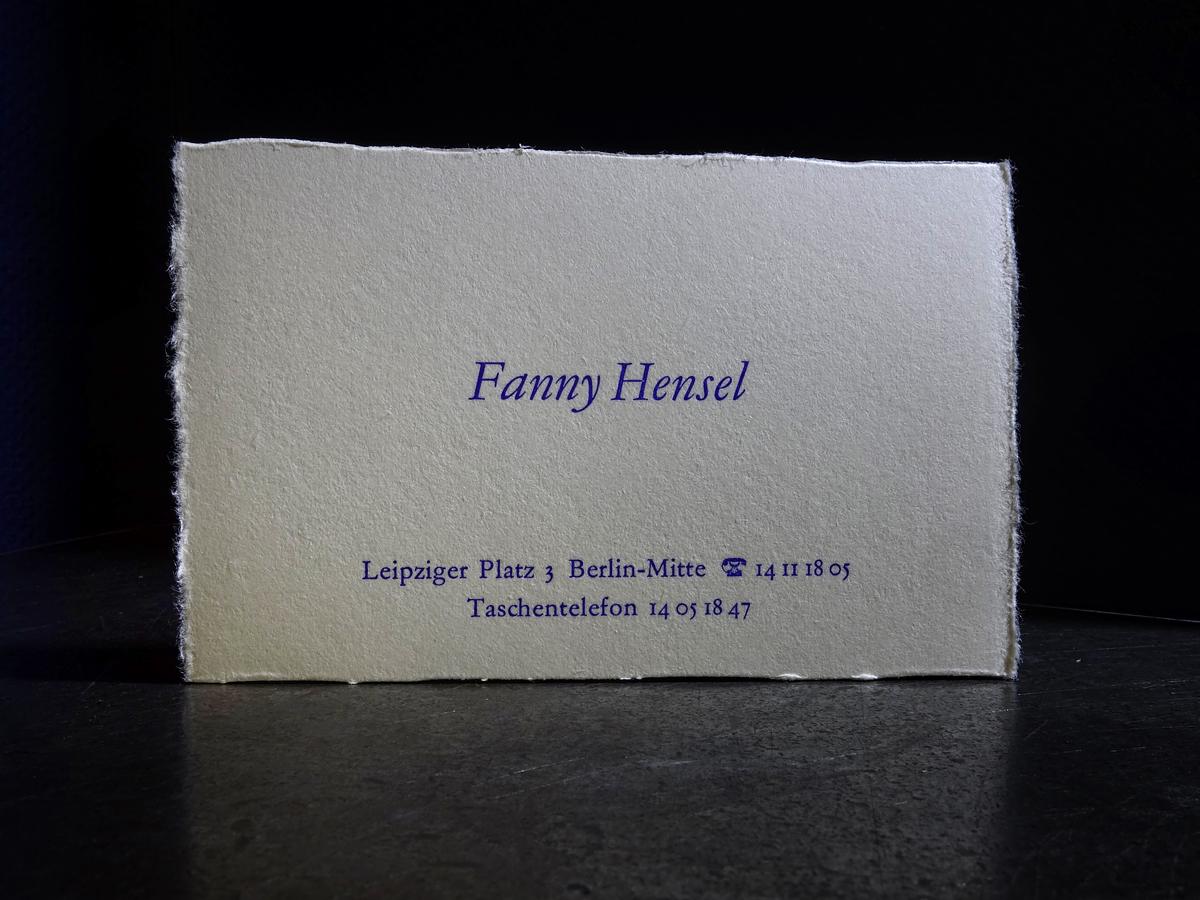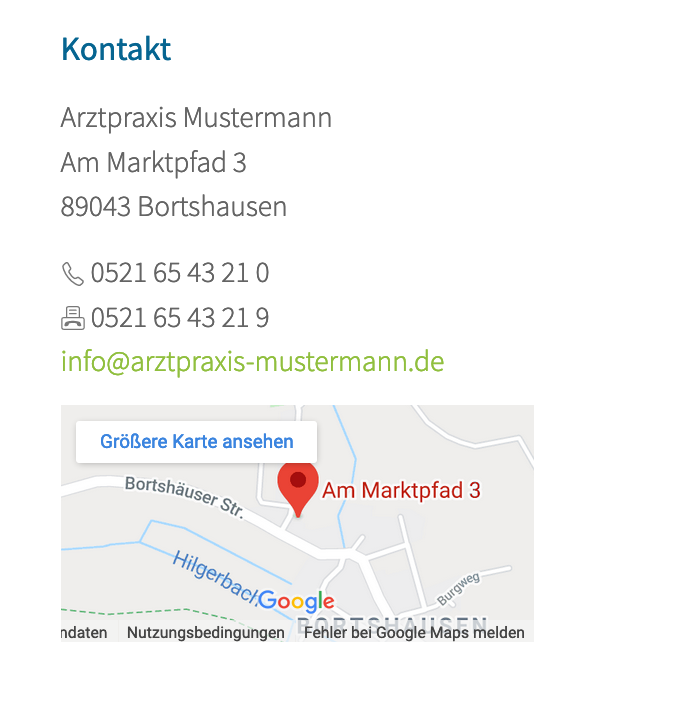
Kennzeichnung einer Faxnummer per Symbol?
Meinem Auge geht es wie Deinem. Ich finde  und erkenne die Information - in diesem Kontext - schneller als mit textuellen Etiketten.
Auf der richtigen Website lasse ich übrigens die URL weg, weil ich sie redundant finde.
Mit Hilfe eines Print-Stylesheets lasse ich sie beim Drucken erscheinen.
Auch ich belege nur die Telefonnummer und nicht die Faxnummer mit "href="tel:..."
Die Faxnummer erhält noch ein Title-Attribut, welches beim Überschweben "Faxnummer" anzeigt.
Zur Verspieltheit: Würdest Du denn soweit gehen, dass bei einer nüchternen Schrift, Farbgebung und Gestaltung generell Symbole für diesen Zwecke unpassend sind?
Wahrscheinlich ja. Zumindest bei einer ansonsten so nüchternen, technischen, sachlichen Gestaltung wie deiner hier. Decke ich die Symbole ab, habe ich diesen Eindruck. Der Symboleinsatz bricht das für mich völlig auf. Aber eben nur an dieser einzigen Stelle – der natürlich notwendigen Unterscheidung zwischen Tel.- und Faxnummer.
Wäre es meine Gestaltung, würde ich meinen, mich jetzt entscheiden zu müssen: entweder dazu, den kühlen Gesamteindruck so beizubehalten (dann eher ohne Symbole) oder die Anmutung bewusst, dann aber konsequent, etwas aufzuweichen. Das müsste dann aber an mehreren Punkten erfolgen. Und da finde ich die Idee mit mehreren Symbolen interessant.
Eine Sache, die ich in dem Zusammenhang übrigens immer hässlich finde, ist diese Geschichte:
Ihhhh! Da könnte man doch mit Symbolen arbeiten, z.B.
… und natürlich nur eine Zeile für beide Angaben. Und mit Symbolen aus einem Symbolfont, nicht mit Emoji. Klick auf 📧 = Email, Klick auf 🌐 = Web.
Und die Postadresse bekommt dann so einen Pin wie aus dem Karten-Apps.
Oder kennst Du weniger verspielte Symbole?
Einen Link habe ich so auf die Schnelle nicht zur Hand, aber zumindest kann ich mir solche Symbole vorstellen, besonders für das Fax. Da ist m.E. tatsächlich zu viel los. Was ist die Grundfunktion eines Faxgeräts, in Abgrenzung von Sprachtelefonie? Da kommt Papier raus. Ein extrem reduziertes  Blatt Papier reicht im Kontext also. Den Hörer für die Telefonnummer könnte man vielleicht noch leicht abstrahieren.
So darfst du im Web aber sowieso nicht denken. Das sieht bei jedem Betrachter anders aus.
Auf  Websites setze ich strikt alle klickbaren Links innerhalb von Fließtext in einer anderen Farbe als diesen. Nicht, weil ich es am schönsten finde, sondern weil es am besten nutzbar ist.
Wie handhabt ihr das innerhalb von solchen Kontaktangaben? Ebenso? Oder verzichtet ihr in diesem engen Kontext darauf?
Kommt drauf an. Früher war ich da auch sehr konsequent (immer Kennzeichnung), aber mittlerweile ist es üblich, dass Devices (ggf. auch ohne dass der Webautor das vorgesehen hat) angetippte Adressen oder Telefonnummern immer laden, so dass immer mehr Anwender da eben auch ohne besondere Einladung drauf klicken werden, besonders wenn es, wie hier in einen Kontaktblock, offensichtlich ist, was der Text darstellt.
Technisch und sachlich kann man alle 5 Informationsen mit einem klickbaren Ziel hinterlegen. Die Postadresse mit einem Google-Maps-Link, URL und Mail ist klar. Und die Telefon- und Faxnummer mit "href=mailto:...".
Du meinst sicher tel:+49… bei der Telefonnummer. Gibt es eine entsprechende Notation für Faxnummern? :-?(durch späteren Beitrag hinfällig geworden)
Ich finde  und erkenne die Information - in diesem Kontext - schneller als mit textuellen Etiketten.
Genau darum geht es. Durch die Verwendung von Symbolen wird aus der notwendigen Unterscheidung zwischen Tel.- und Faxnummer eine Hervorhebung dieser beiden Nummern. Aber warum werden nur die hervorgehoben, Email- und Postadresse aber nicht? :-?
"T" oder "Tel" ist für mich ein Etikett, eine Sonderbehandlung.
Bezogen auf z.B. die Mailadresse.
Klar, wenn der Rest nicht etikettiert ist, ist die Erklärung durch das Etikett schon eine Sonderbehandlung.
Für Dich liegt offenbar erst dann eine Sonderbehandlung vor, wenn ein Symbol verwendet wird, statt Text.
Wenn in einem rein textlichen Umfeld auch noch Symbole verwendet werden, ist es in diesem Fall quasi eine doppelte Sonderbehandlung (Etikett + Symbol) und dadurch eine sehr starke Auszeichnung. Diese Auszeichnung könnte man abschwächen in dem man eine ›Sonderbehandlung‹ weglässt – welche wäre wohl sinnvoller?!
Gibt es für Dich, gehen wir mal weg von den Kontaktdaten, keinerlei Situationen, wo Du eine Kennzeichnung mit Symbolen statt textuell befürworten würdest?
Warum diese Frage? Natürlich gibt es Situationen, in denen ich Symbole besser finde – auch im Bereich Kontaktdaten. Das hatte ich auch bereits geschrieben ...
Mein Fazit: lass die Symbole weg oder passe deren Größe an, wenn sie aus Deiner Sicht unbedingt notwendig sind.